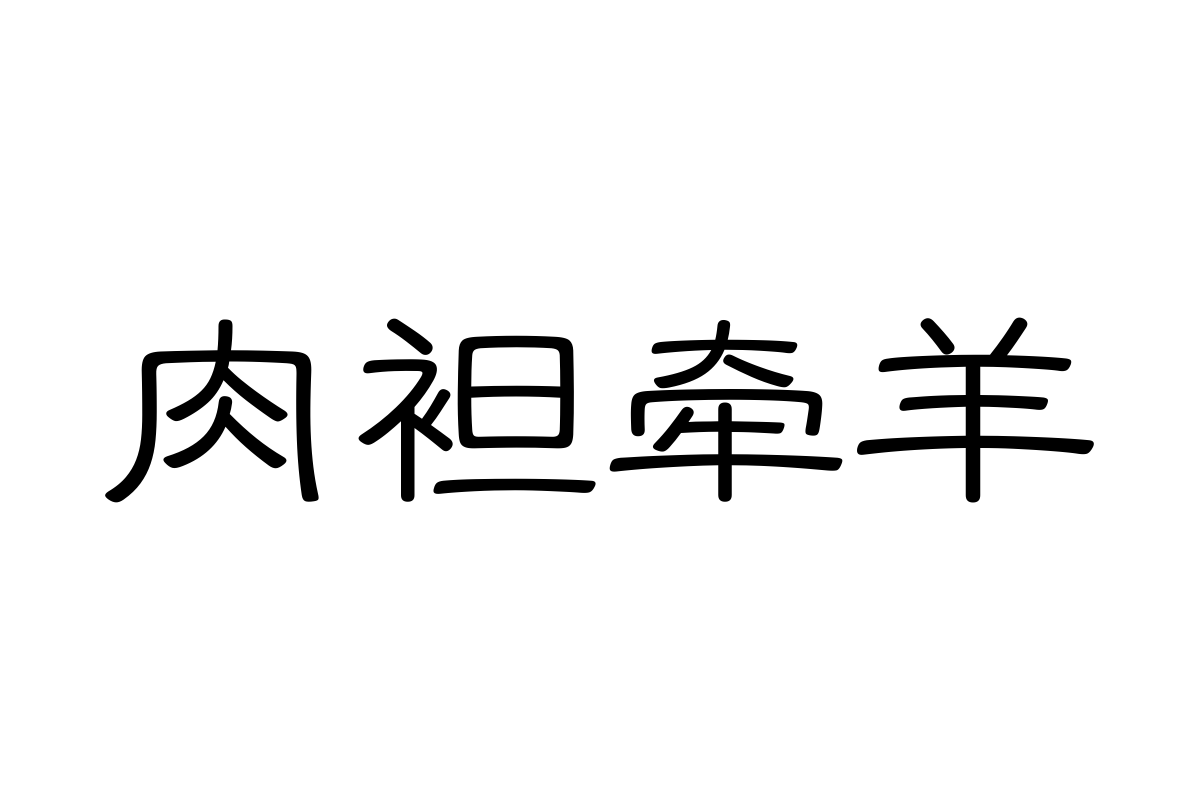
汉仪玉筋隶45字体是一款具有独特韵味的书法字体,其笔画流畅、结构严谨,适合用于各种书写和设计场景。该字体由汉仪公司精心打造,融合了传统书法艺术与现代设计理念,使得其在保持原汁原味的同时,又不失时尚感。
汉仪玉筋隶45字体的特点如下:
1. 笔画流畅:该字体的笔画线条顺滑,给人一种优雅的感觉,非常适合用于书写和设计。
2. 结构严谨:字体的结构紧凑有序,每个笔画都恰到好处地分布在字形中,使得整个字体看起来更加整齐划一。
3. 风格独特:汉仪玉筋隶45字体在保持传统书法韵味的同时,还融入了一些现代元素,使得整体风格既古典又时尚。
4. 适用范围广泛:该字体适用于各种书写和设计场景,如海报、宣传册、网站等,都能展现出其独特的魅力。